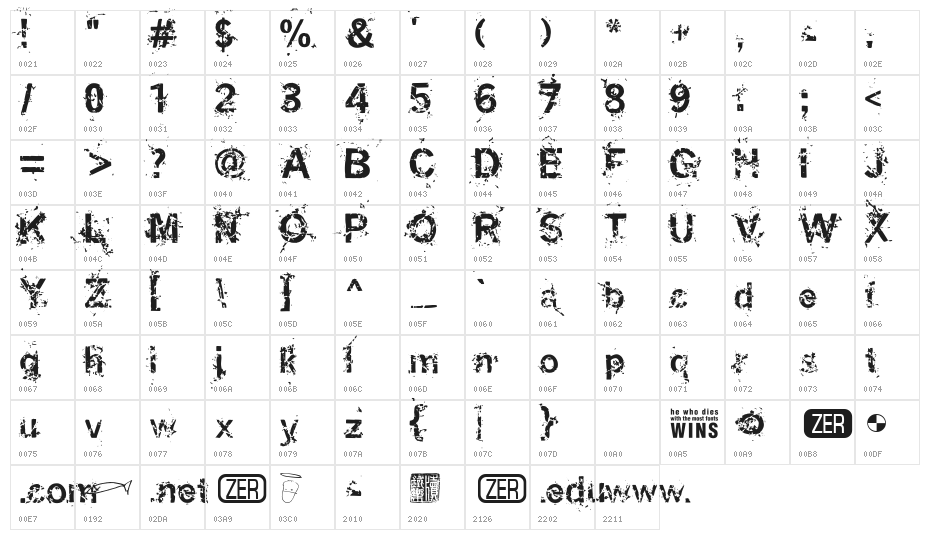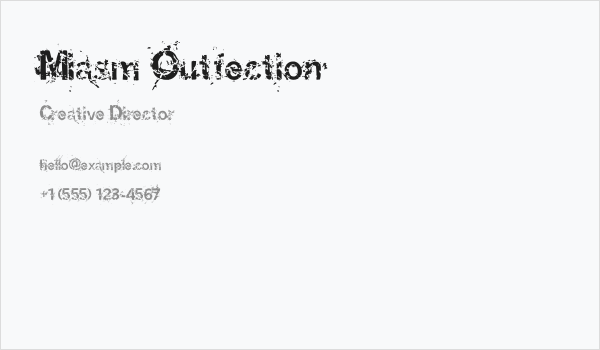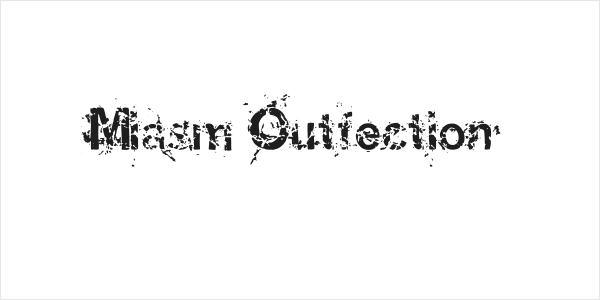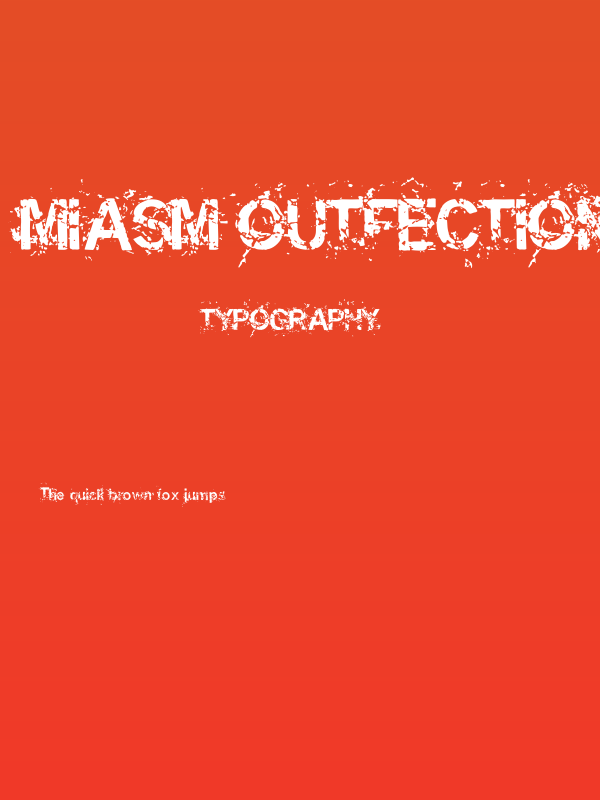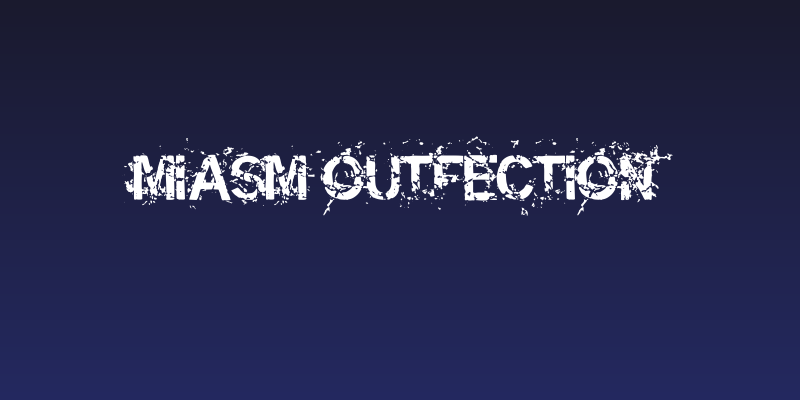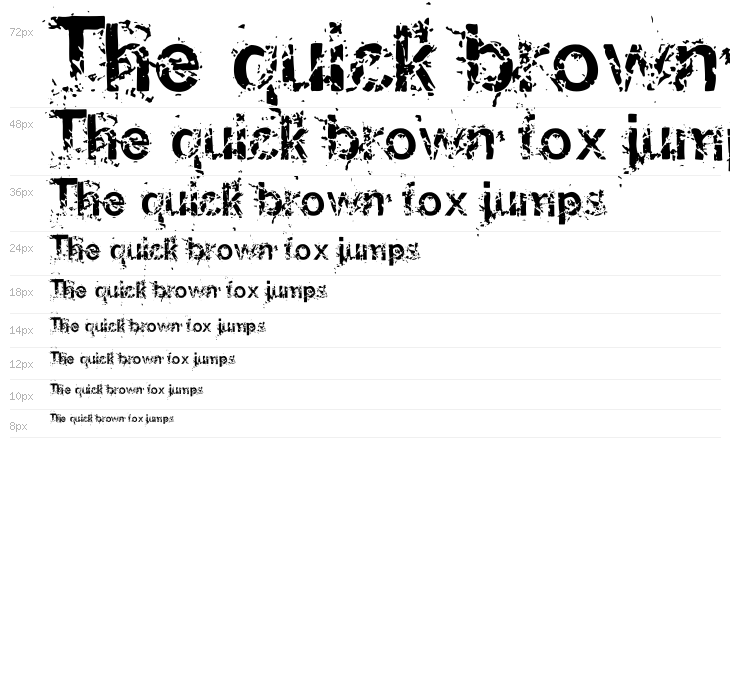
Miasm Outfection Font
✎ Distorted Eroded
| Категория | Distorted Eroded |
| Общий стиль | Grunge, Urban, Edgy |
| Рекомендуемые проекты | Ideal for music album covers, streetwear branding, event posters, or any project needing a bold, edgy aesthetic. |